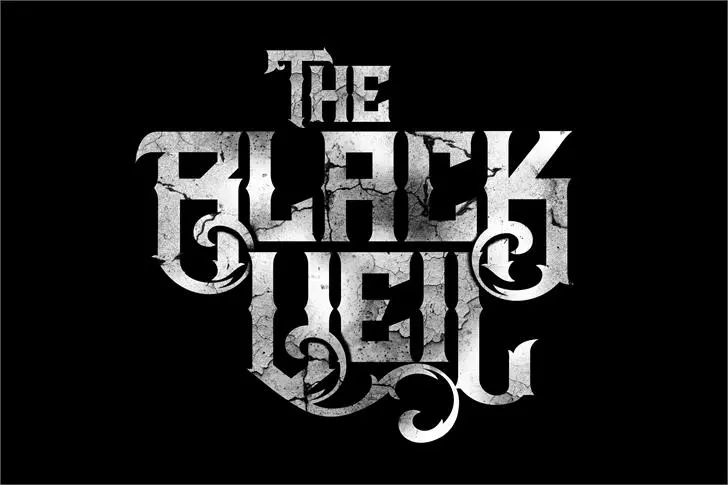
A Black Veil font é uma criação do designer Hamilton lançada em 2014. Essa fonte Blackletter, conhecida pela sua aparência elegante e única, oferece um toque distintivo para qualquer projeto de design gráfico. Seu estilo medieval dá ao texto um ar elegante que se destaca, seja você criando materiais para uma publicação literária ou estabelecendo o tom de uma marca empresarial. A Black Veil traz consigo nuances sutis de cor e espessura, permitindo-lhe explorar diferentes tonalidades sem comprometer a seriedade requintada da sua fonte base. Ideal tanto para uso em materiais impressos quanto em aplicativos digitais, essa fonte é uma escolha inteligente para quem busca um recurso gráfico que seja ao mesmo tempo estiloso e elegante.